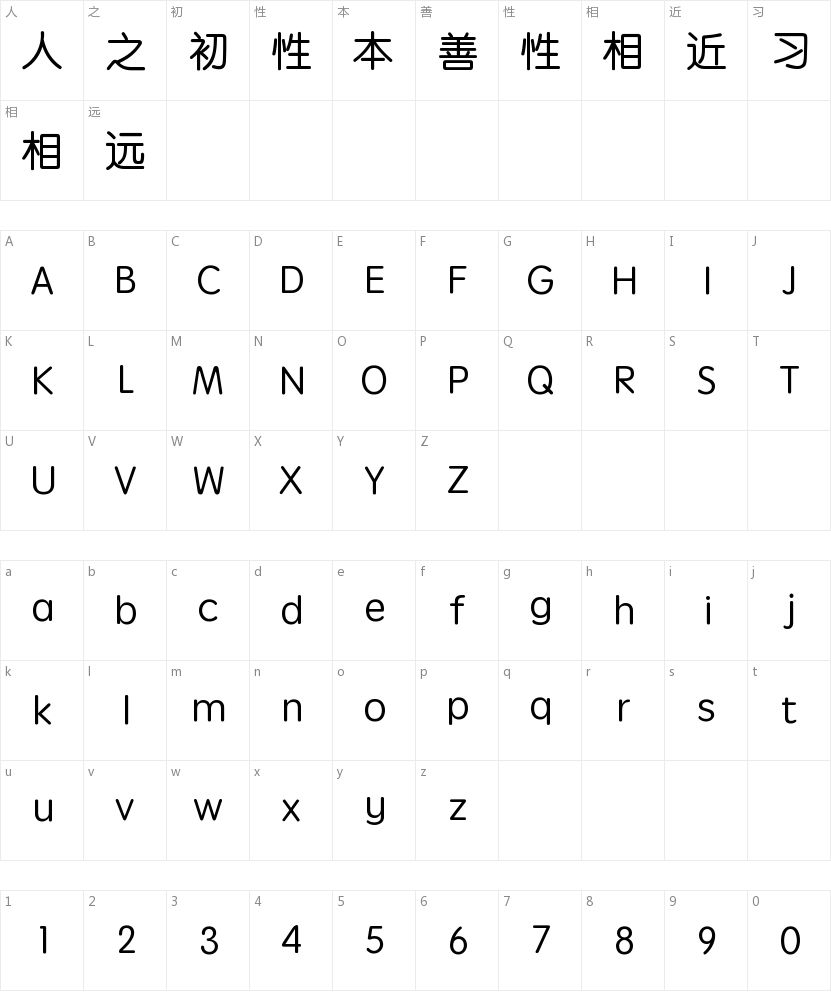
风雨 华文圆体
风雨华文圆体是一款中文字体,由中国著名字体设计师陈慧琳设计,于2004年发布。它的字形采用圆形的设计,笔画细腻,笔划流畅,字体造型清新大方,在汉字书写中表现出宽松的气氛,具有极强的视觉冲击力。使用风雨华文圆体可以让文字拥有更加柔和的视觉效果,更能够体现出文字的美感,是一款非常适合用于文字设计的字体。
风雨 华文圆体是一款非常不错的手写艺术字体,具有很好的视觉感,适合于文化类的宣传设计、商业类品牌的广告和产品包装设计以及个性化文字排版等较多场景。